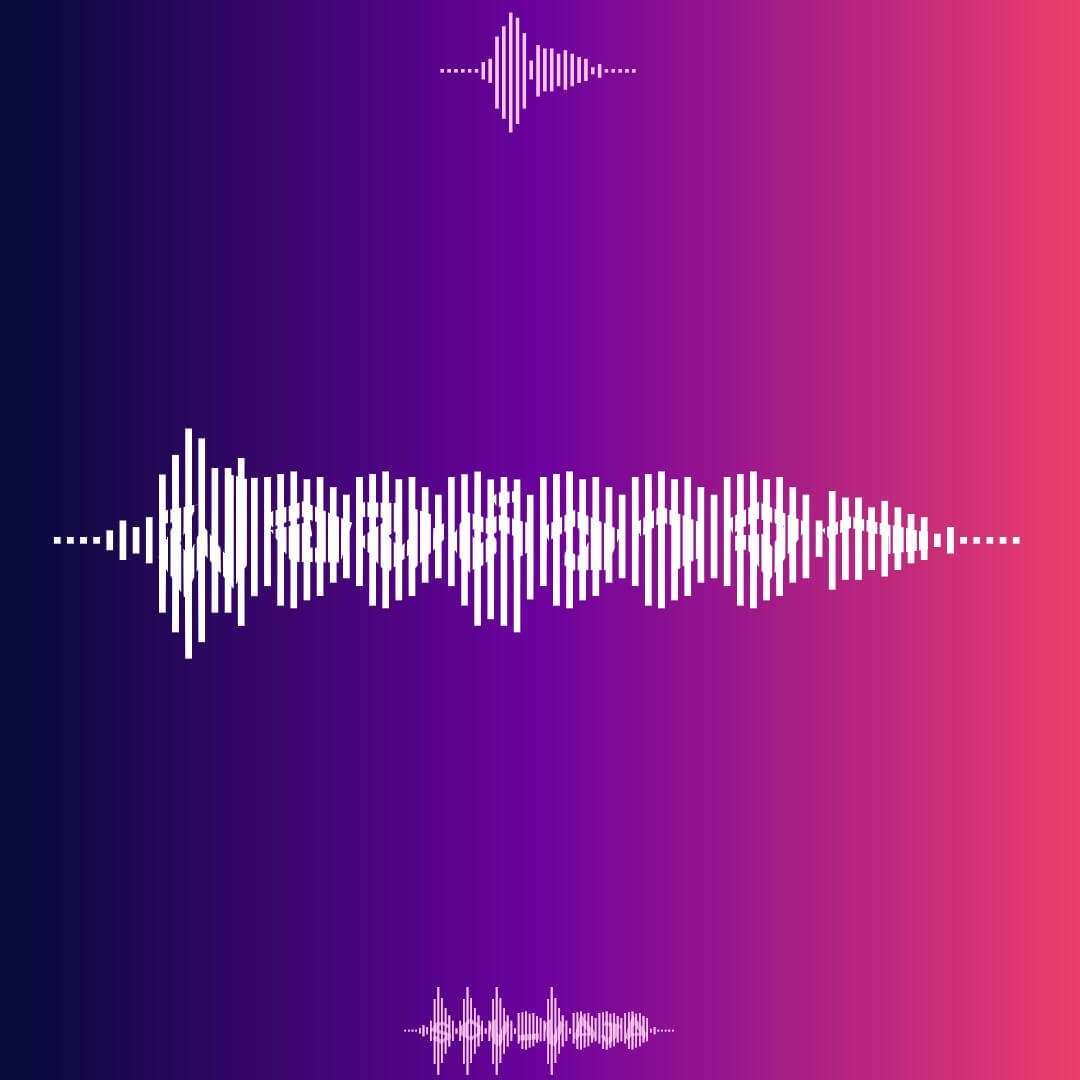
บันได (SOV_BanDai)
ฟอนต์บันได – ฟอนต์แนวราบ ยกพื้น เป็น 3 มิติ มีบันไดให้ขึ้น ทั้งซ้ายขวา …พิมพ์วงเล็บ จะได้บันได
ฟอนต์แพรพรรณ – เป็นฟอนต์ริบบิ้นอีกแบบหนึ่ง อาจเรียกว่าเป็นธง เป็นผืนผ้า น่าจะเหมาะกว่า ใช้เป็น logo font … แต่จะใช้กับประโยคก็ได้ ยังไงก็สะดุดรอยพับอยู่แล้ว
ฟอนต์ ฟิ้ววววว – ฟอนต์ตัวนี้ให้นึกภาพว่า เอาแปรงทาสีร่างตัวอักษรเสร็จ แล้วเอากิ่งไม้เล็กๆ ลากขวาง… ฟิ้ววววว (ตัวปรกติฟิ้วววววไปขวา ตัวหนาฟิ้วววววไปซ้าย)
ฟอนต์กระแทก – ใช้ ฯฯ หน้าอักษรที่อยากให้ถูกกระแทก แตกได้ 1-5 ตัวอักษร
ฟอนต์วาจา – อักษรบนรูปคลื่นเสียง อักษรไทยพิมพ์ได้ปรกติ เว้นวรรคแยกคำหรือประโยค อักษรละตินใส่ไว้ในปีกกา { }
ฟอนต์ช่องไฟ – สำหรับฟอนต์… ช่องไฟสำคัญ แต่ไม่มีใครเห็น ก็เลยทำฟอนต์ให้ช่องไฟ… สรุปเห็นช่องไฟ แต่ไม่เห็นตัวอักษรแทน …ฮา
ฟอนต์คาดพุง – อักษรเว้นที่ว่างตรงกลาง ใส่วงเล็บเป็นริบบิ้น
ฟอนต์สัญญาณ(ชีพ)
ฟอนต์วัดบูรณาราม – ฟอนต์นี้ต้นทางมาจาก ใบลาน วัดบูรณาราม สี่แยกท่าวัง อ.เมือง จ.นครศรีธรรมราช เป็นอักษรไทยสมัยอยุธยา (ส่วนช่วงเวลาใดไม่ปรากฏในเอกสาร ต้องลองพิจารณาศึกษาเพิ่มเติมกันเอาเอง)
ฟอนต์เงาอดีต – งานทดลองฟอนต์ 2 ชั้น อักษรไทยตัวบนต้นแบบจาก จารึกหลักที่ ๑ ส่วนตัวล่างอักษรปัจจุบันแบบหัวเปิด เพื่อให้เห็นการเปลี่ยนรูปอักษรจากในอดีตมาปัจจุบัน ส่วนอักษรที่มีความคล้ายกันหรือไม่ทำให้สับสน จะทำการยึดอักษรเพื่อเป็นการแสดงให้เห็นความคงอยู่ หรือเปลี่ยนแปลงที่ค่อนข้างน้อย
ฟอนต์สะพาน – แนวอักษรสัมพันธ์ คราวนี้ข้ามคลอง ลอดอุโมงค์ ไปเจอกันจนได้ (ถ้าอยากกีดกันสานสัมพันธ์ ให้กด ฯฯ แทรกกลางเช่นเคย)
ฟอนต์น้อยๆ – เป็น logo font ตัวอักษรน้อยๆ แนะนำไม่เกิน 5 ตัวอักษร เพราะตาเราจะเริ่มแยกแยะไม่ออกแล้ว
ฟอนต์น้ำหนัก – ทำอักษรวูบวาบ จากการไล่น้ำหนัก และ/หรือ ไล่ความกว้าง เหมาะใช้แค่เป็นพิ้นหลังข้อความเยอะๆ และไม่ต้องการอ่านข้อความเหล่านั้น 55 …กด bold ได้อีกแบบ
ฟอนต์ยี่ห้อ – ทดลองทำ sarif font ปรกติ ให้เป็น logo โดยใช้ตัวพิเศษ (กด ฯฯ เหมือนเดิม)
ฟอนต์ร่างแบบ – พาเบื้องหลังมาไว้เบื้องหน้า แต่ว่าเหมาะแค่คำสั้นๆ